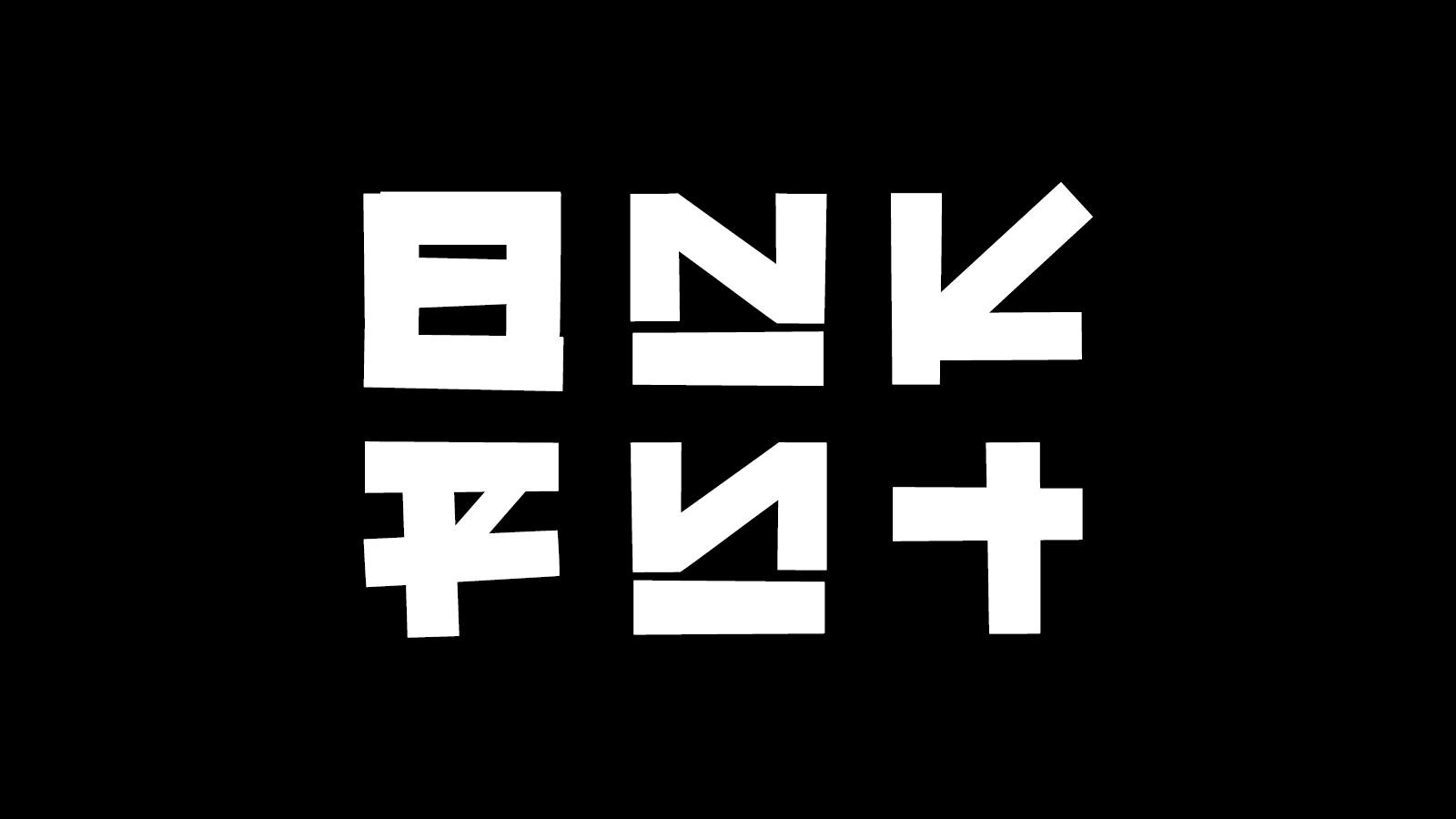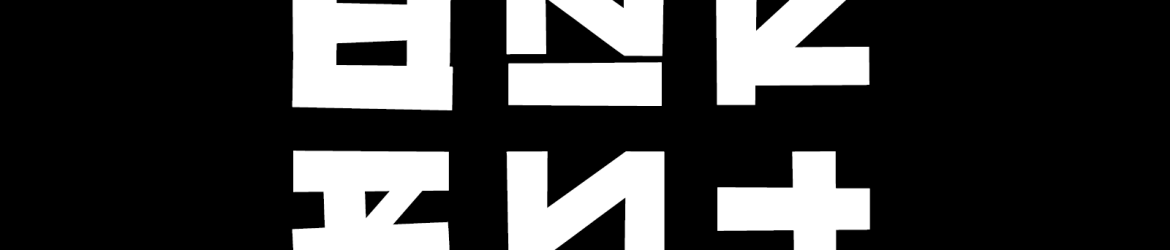
Aqui está uma descrição para a página de download da font ‘Bankay Font’ na categoria de Graffiti Fonts: O design do graffiti é sempre uma forma vibrante e expressiva de comunicação urbana. A fonte ‘Bankay Font’ é um exemplo perfeito desta linguagem visual, repleta de movimento e grafiato. Com linhas dinâmicas e tipografia em relevo que refletem a essência dos murais urbanos, essa fonte traz uma sensação vibrante e atemporal para qualquer projeto. Especialmente adequada para aqueles amantes da cultura urbana ou designers de grafite em busca de um elemento único e forte, ‘Bankay Font’ é perfeita para marcar espaços publicitários, criar selos únicos ou adicionar personalidade a qualquer tipo de design. E como o graffiti reflete a essência do espírito da cidade onde vive, esta fonte traz uma dimensão especial à qualquer trabalho visual. Obrigado ao designer mrkmra por compartilhar seu talento e criar algo tão emocionante para nossa comunidade de designers e artistas. Descubra agora como ‘Bankay Font’ pode transformar seus projetos em verdadeiras obras de arte urbana.